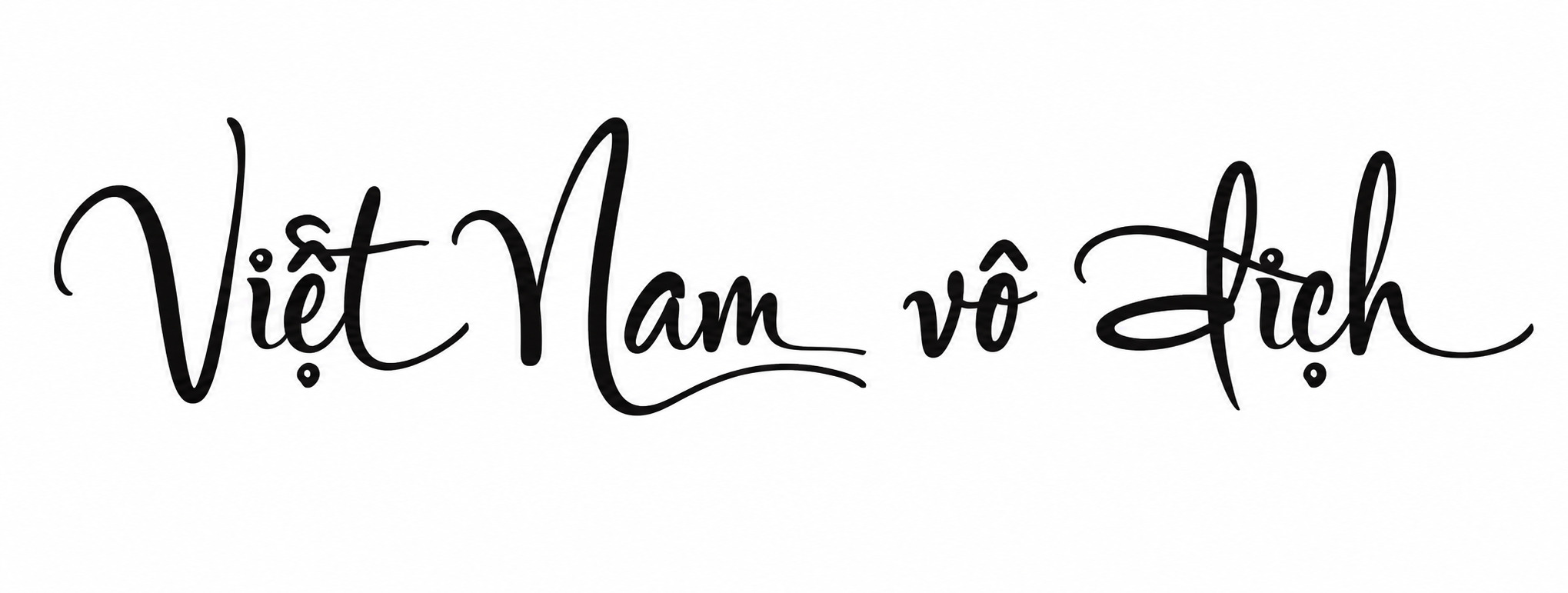
Nhiều designer tìm Font Fz Tiểu Tự Việt hóa hay gặp lỗi thiếu dấu tiếng Việt hoặc các nét bút lông nhỏ bị nhòe, mất chi tiết khi in ấn hộp trà đạo cao cấp. Những lỗi kỹ thuật này khiến thiết kế mất đi vẻ thanh tịnh, an yên vốn có, làm giảm tính trang trọng của món quà truyền thống trong mắt người nhận.
Font Fz tiểu tự là gì?
Trong nghệ thuật thư pháp Á Đông, “tiểu tự” là thuật ngữ chỉ lối viết chữ chân phương cỡ nhỏ bằng ngòi bút lông thanh mảnh, đòi hỏi sự điềm tĩnh, mực thước và chuẩn mực trong từng nét hạ bút. Khác với lối đại tự cuồn cuộn khí thế, tiểu tự mang vẻ đẹp khiêm nhường, tĩnh lặng và đậm chất thiền định. Nằm trong Bộ font Fz Việt hóa danh tiếng của cộng đồng yêu chữ truyền thống, phông chữ mô phỏng chân thực từng nhịp điệu của sợi lông cọ, nét mực loang nhẹ nhàng và độ sắc sảo của những đoạn nhấn bút tinh tế.
Điểm giá trị của Fz thư pháp tiểu tự là sự phù hợp dành cho các ấn phẩm mang tính hoài niệm, tâm linh, y học cổ truyền và văn hóa dân gian. Bản gốc được tác giả Fz tạo tác đã tinh chỉnh đồng bộ hệ thống dấu thanh tiếng Việt theo chuẩn Unicode, khắc phục hoàn toàn tình trạng dấu mũ bị vỡ hạt hay lệch khỏi khung chữ. Nhờ đó, người làm thiết kế có thể dễ dàng ứng dụng vào các đoạn văn bản dài, lời đề từ hoặc thơ ca trên bao bì mà vẫn giữ được tính trang nhã, dễ đọc.
Lưu ý: Font Fz tiểu tự mang vẻ đẹp mộc mạc và tĩnh lặng. Khi dàn trang hộp quà tặng trà shan tuyết hoặc trầm hương, bạn nên phối hợp cùng chất liệu giấy Kraft nâu, giấy mỹ thuật có gân xơ tự nhiên để tôn vinh trọn vẹn tinh thần văn hóa của phông chữ này.
5 ứng dụng Font Fz Tiểu Tự Việt hóa trong thiết kế và in ấn
Nhờ phong cách thư pháp phương Đông, nét chữ mềm mại cùng cảm giác tĩnh tại, Font Fz Tiểu Tự Việt hóa được ứng dụng linh hoạt trên nhiều sản phẩm bao bì và quà tặng doanh nghiệp mang yếu tố truyền thống:
- Thiết kế bao bì hộp trà đạo và sản phẩm dưỡng tâm: Font Fz Tiểu Tự phù hợp để thể hiện thơ, câu đối, tên sản phẩm hoặc lời đề tự trên hộp trà cao cấp, hộp trầm hương. Các nét chữ thanh thoát giúp bao bì tạo cảm giác an yên, tinh tế và giàu giá trị văn hóa.
- Sản xuất bao bì hộp quà Tết và bánh Trung thu cao cấp: Khi kết hợp cùng giấy mỹ thuật, ép kim nhũ vàng hoặc dập nổi, Font Fz Tiểu Tự giúp hộp quà mang vẻ trang trọng, phù hợp với các dòng quà biếu dành cho khách hàng, đối tác hoặc người lớn tuổi.
- In ấn sách, lịch bàn và ấn phẩm nghệ thuật: Font chữ tiểu tự được ứng dụng trong các thiết kế liên quan đến thơ ca, hội họa, văn hóa truyền thống hoặc ấn phẩm lưu niệm, giúp tổng thể sản phẩm giữ được nét cổ điển và giàu cảm xúc.
- Khắc laser quà tặng gỗ và tre: Các đường nét thư pháp của Font Fz Tiểu Tự khi khắc trên hộp trà gỗ, ống tre, sổ tay hoặc vật phẩm trang trí giúp tạo điểm nhấn thủ công, phù hợp với các sản phẩm quà tặng mang tính cá nhân hóa.
- Trang trí nhãn dán sản phẩm thủ công: Font Fz Tiểu Tự phù hợp với nhãn giấy Kraft, giấy mỹ thuật cho các sản phẩm như mật ong, thảo dược, trà khô hoặc đồ thủ công, giúp thương hiệu truyền tải hình ảnh mộc mạc và đáng tin cậy.
5 lưu ý khi sử dụng Font Fz Tiểu Tự Việt hóa
Để Font Fz Tiểu Tự Việt hóa giữ được vẻ đẹp thư pháp khi đưa vào sản xuất thực tế, designer cần chú ý các yếu tố kỹ thuật sau:
- Kiểm soát độ mảnh của nét bút: Font Fz Tiểu Tự có nhiều nét thanh và chi tiết mô phỏng bút lông. Khi in trên giấy Kraft hoặc giấy mỹ thuật có độ hút mực cao, nên kiểm tra kích thước chữ để hạn chế tình trạng mất nét.
- Tối ưu đường Path cho gia công dập nổi: Khi sử dụng Font Fz Tiểu Tự để dập nổi câu chữ hoặc logo trên hộp quà cao cấp, các đường cong và điểm giao nhau trong file vector cần được xử lý gọn gàng. Điều này giúp khuôn dập thể hiện rõ từng chi tiết, hạn chế lỗi biến dạng trong quá trình gia công.
- Điều chỉnh khoảng cách dòng và bố cục chữ: Với các câu đối, bài thơ hoặc nội dung nhiều dòng, designer nên tạo khoảng cách dòng phù hợp để chữ có không gian thể hiện, tránh làm mất đi sự nhẹ nhàng của phong cách thư pháp.
- Lựa chọn màu sắc in phù hợp: Font Fz Tiểu Tự thường phù hợp với các màu sắc mang tính truyền thống như đen, đỏ son, nâu đất hoặc ép kim vàng. Những gam màu này giúp làm nổi bật vẻ trang trọng của bao bì.